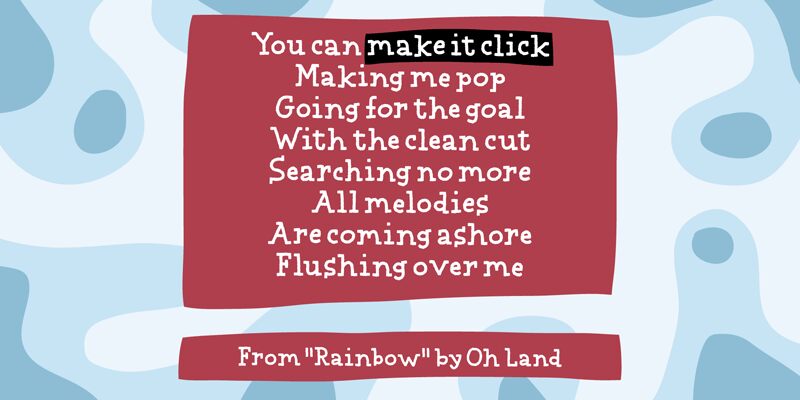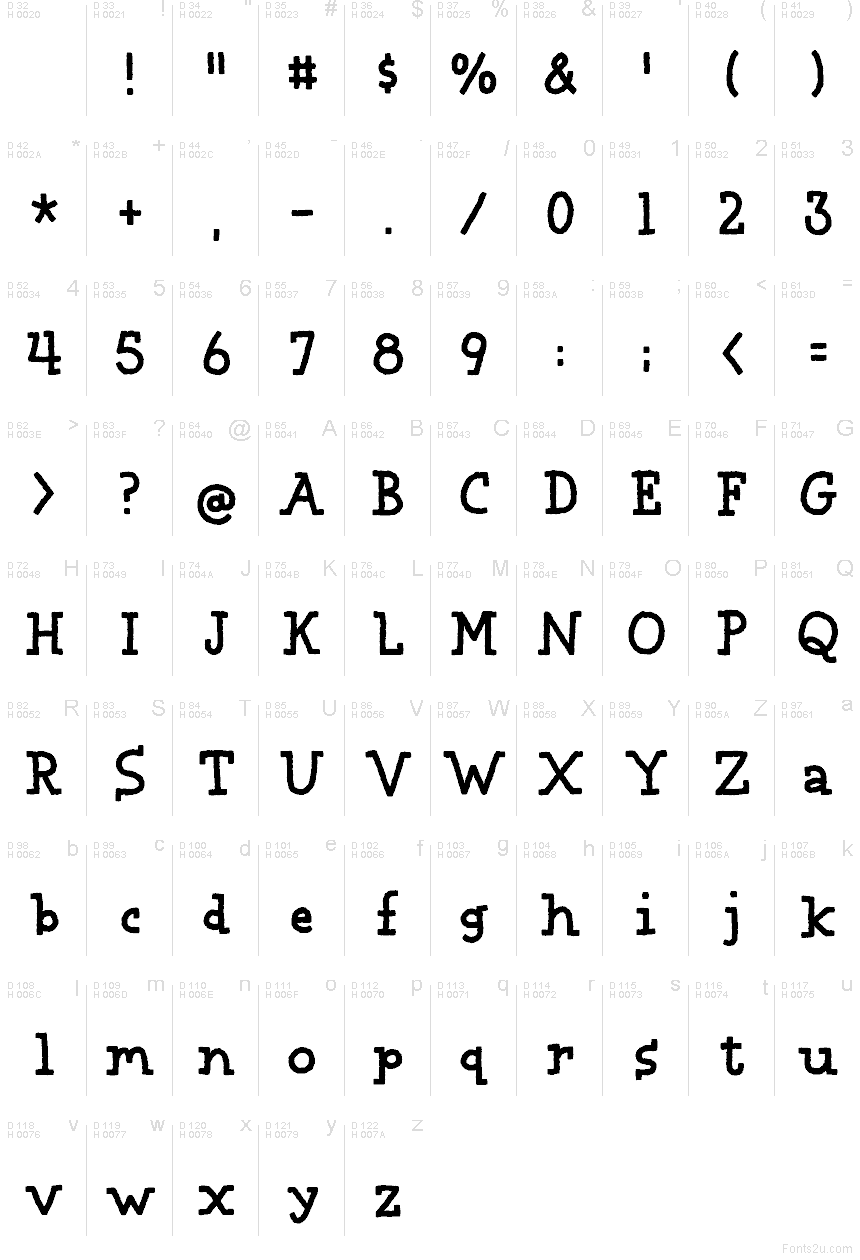
Make It Click DEMO Regular
Make It Click von Jakob Fischer ist eine kostenlose Cartoon-Display-Schriftart mit handgezeichnetem Scherenschnitt-Look. Die Buchstaben wirken wuchtig und leicht wackelig – mit rauen Kanten, ungleichmäßiger Strichstärke und einer verspielten Dynamik, die das gesamte Alphabet wunderbar ungezwungen und lebendig wirken lässt.
Sie passt perfekt zu Scrapbook-Titeln, Kinderbuch-Covern, Comic-Überschriften, Bastelverpackungen und verspielten Plakattexten, bei denen die handgemachte Unregelmäßigkeit für eine direkte, menschliche Note sorgt. Als kostenlose Schriftart eignet sie sich zudem hervorragend für schnelle Social-Media-Grafiken, Unterrichtsmaterialien oder kurze Titelkarten, bei denen die dicken, unebenen Formen für sich allein stehen können.
Die VOLLVERSION enthält Kerning, zusätzliche internationale Zeichen sowie häufig auch Ligaturen und kontextabhängige Alternativen.